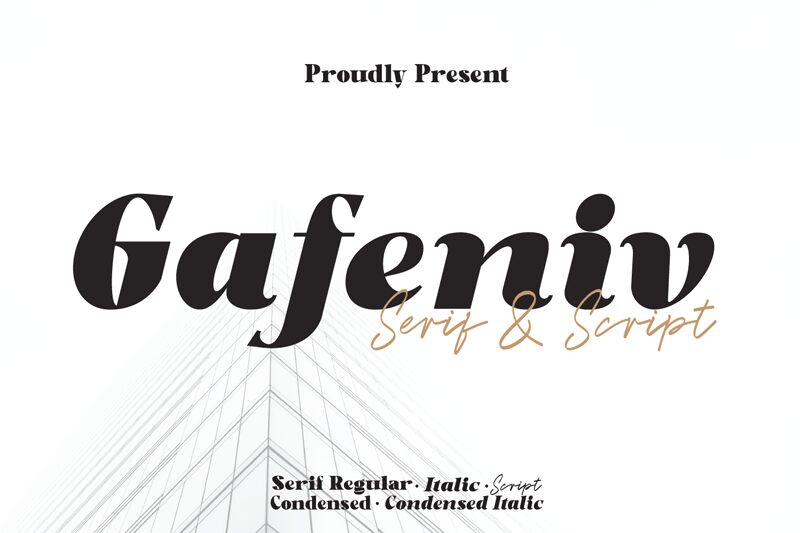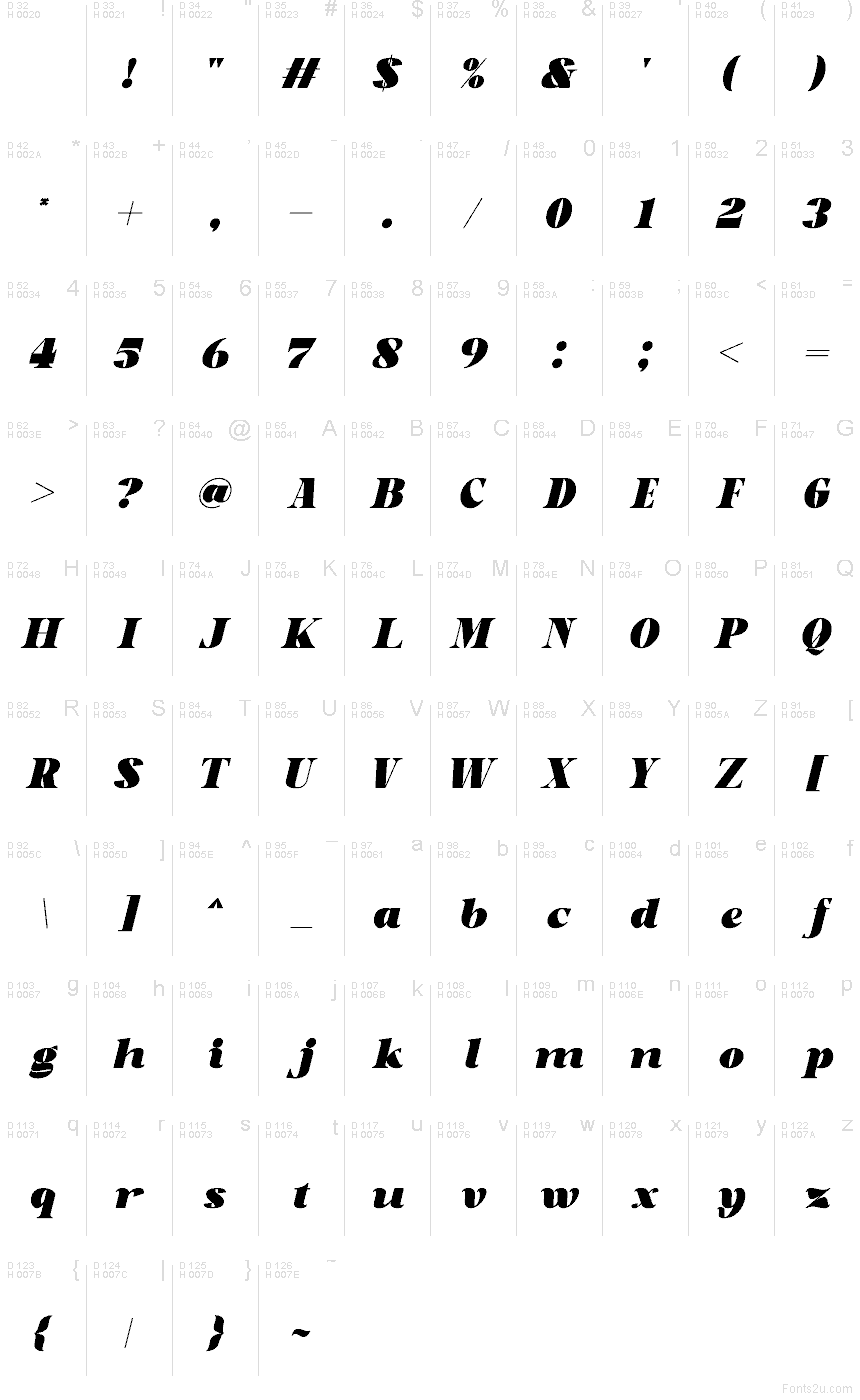
Gafeniv Italic de Rvandtype es una fuente serif gratuita de alto contraste con una pronunciada inclinación hacia adelante. Sus curvas amplias y oscuras se encuentran con trazos ultrafinos, lo que otorga a las letras un marcado perfil editorial de moda. Diversas formas se extienden en trazos largos y fluidos.
Los diseñadores que trabajan en moda y belleza la encontrarán adecuada para portadas de revistas y envases de perfumes. Sus proporciones condensadas también aportan dramatismo a carteles de eventos. Los contornos fluidos pueden evocar los pliegues de las telas o la fotografía de producto, haciendo que la tipografía forme parte de la propia imagen.